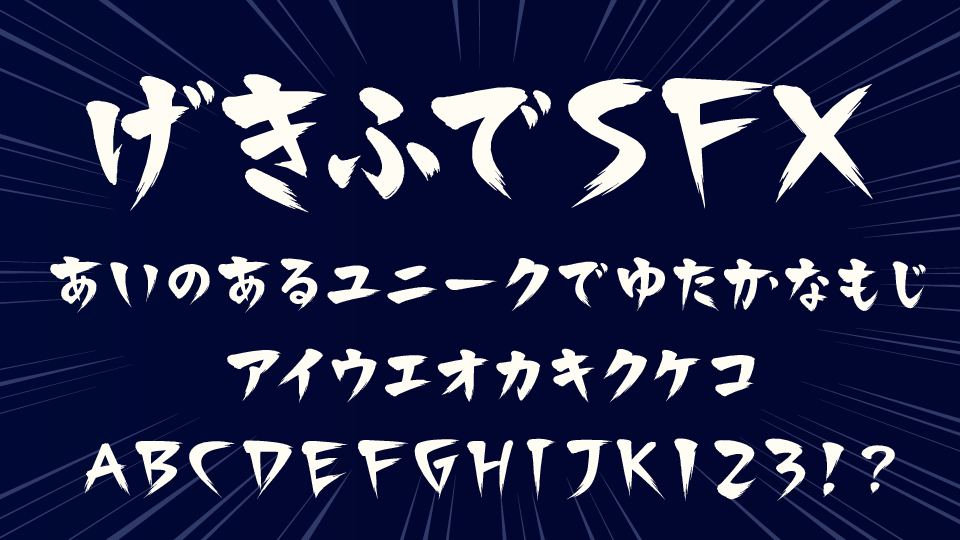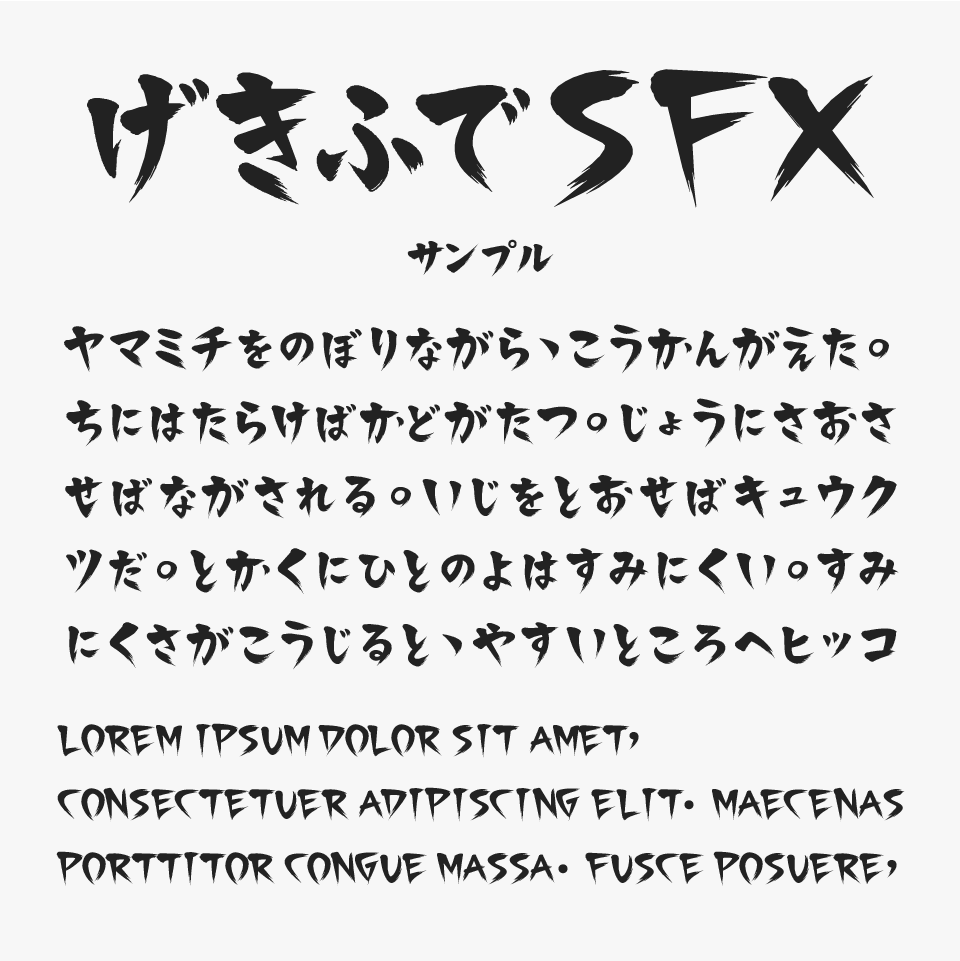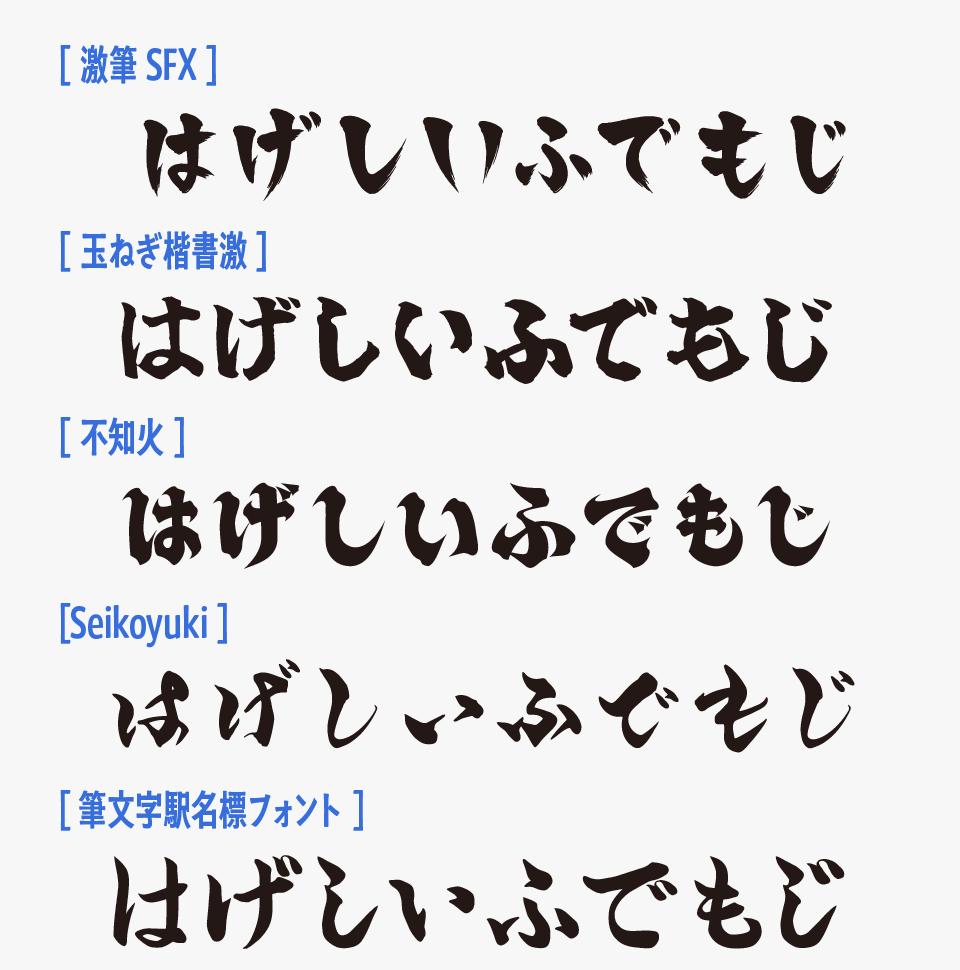
激筆 SFXフォントは、勢いよく筆を振り下ろしたような鋭いハネや払いを大胆に取り入れた、迫力あふれる筆文字フォントです。
墨が飛び散るようなダイナミックなシルエットが特徴で、一文字だけでも強い存在感を放ちます。力強さとスピード感を兼ね備えており、熱量や緊張感を一瞬で伝えられるため、インパクト重視のデザインにぴったりです。
漫画・コミックのオノマトペ、効果音、叫び声、衝撃表現を目的としたフォントとして制作されていますが、他にもアクション作品や格闘ゲーム、和風ファンタジー、ホラー、映画のタイトルなど、迫力ある演出を求める場面におすすめなフォントです。
激筆 SFX
激筆 SFXフォントを、ほかの強めな筆文字フォントと比較してみると、効果音や必殺技の演出を意識した、圧倒的な勢いと躍動感が魅力です。荒々しく走る筆致と大胆な文字バランスによって、一瞬の衝撃や爆発的なエネルギーを視覚的に表現にぴったりです。
激筆 SFXフォント、「玉ねぎ楷書激」「不知火」「seikoyuki」「駅名標フォント」を比較